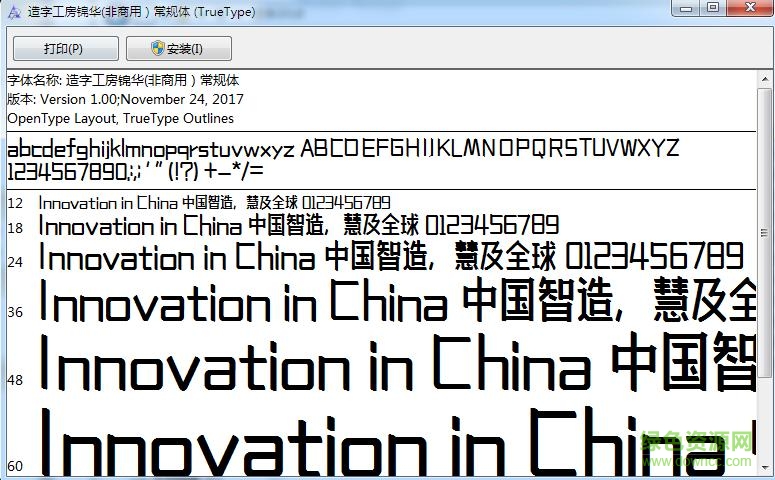
造字工房錦華字體是一款非商用的電腦字體,字形非常簡(jiǎn)潔實(shí)用,美術(shù)設(shè)計(jì)、文字排版等方面都可以使用,有需要的朋友歡迎免費(fèi)下載!
造字工房錦華是造字工房于2017年年末發(fā)布了全新的15款新字體中的一款,這款字體單個(gè)看上去中規(guī)中矩,但是整體看上去就會(huì)有非常鮮明的特色,非常適合用來(lái)進(jìn)行創(chuàng)作!